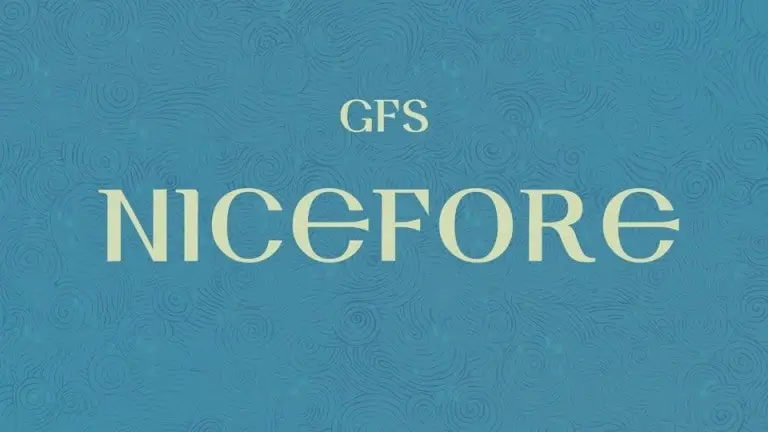
GFS Nicefore Display Font – Fonte Grátis
GFS Nicefore Display Font
A GFS Nicefore Display Font é uma tipografia display que retrata os formadores maiusculos bizantinos típicos dos períodos do século V ao VII. Este estilo se adaptou perfeitamente à nova arte da tipografia e à necessidade de humanistas em reproduzir a antiga era greco-romana. Naquela época, livros gregos eram impressos utilizando uma mão bizantina contemporânea, combinada com letras maiúsculas inspiradas na antiguidade romana – letras com traços grossos e finos e séfus (pontas arredondadas). A tradição de majuscule bizantino permaneceu viva até o início do século XIX. A GFS Nicefore Display é uma fonte perfeita para quem busca incorporar esse estilo arcaico na sua identidade visual, seja em logos ou materiais impressos, criando um resgate dos primórdios da cultura e arte ocidental.